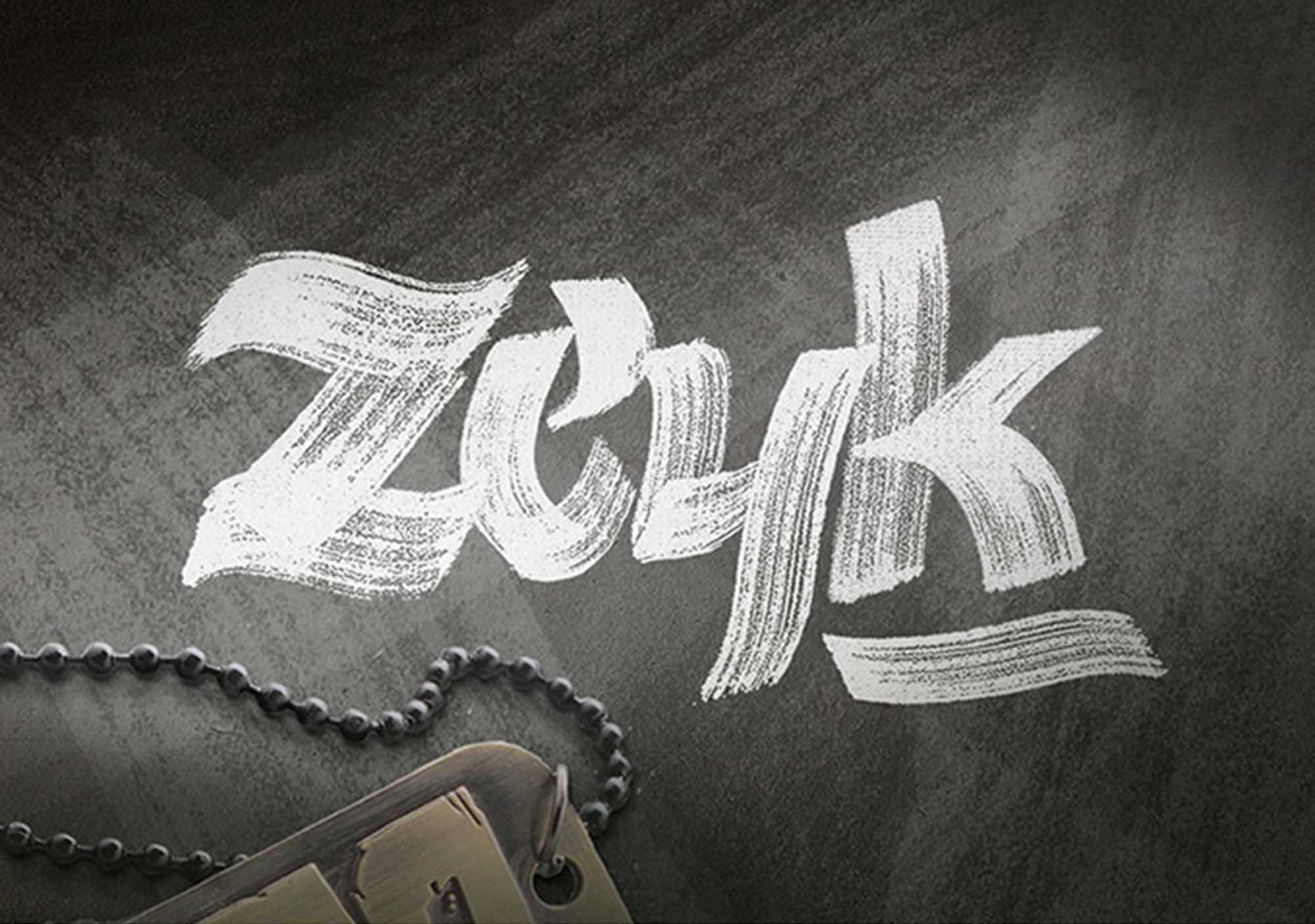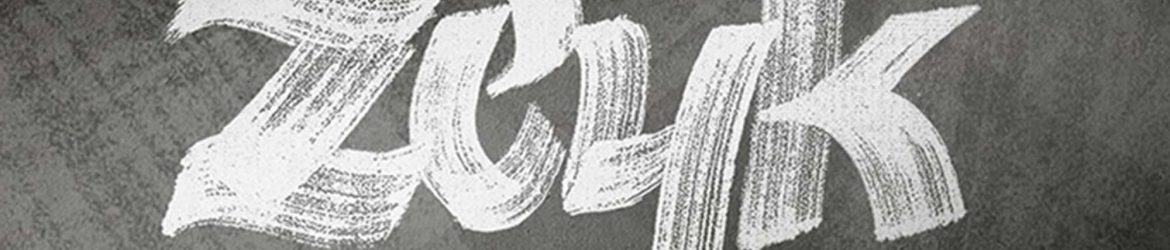
Zeyk Brush Typeface – Download Grátis
A Zeyk Brush Typeface é um recurso gráfico gratuito que oferece uma combinação única de modernidade em um tipo de fonte de esfumar. Ela foi criada com muito carinho e dedicatória por Juan Pablo Bello, um artista talentoso. Este tipo de fonte de esfumar não é apenas bonito, mas também versátil, adequado para diversos projetos. Com sua Zeyk Brush Typeface, você pode adicionar um toque de sofisticação e originalidade a qualquer projeto, seja ele digital ou impresso. Seja para criar uma identidade de marca única, um site atraente ou até mesmo um design de cartão de visita, esta fonte de esfumar é uma ótima opção. A Zeyk Brush Typeface é uma escolha inteligente para quem busca qualidade e beleza em cada caractere.